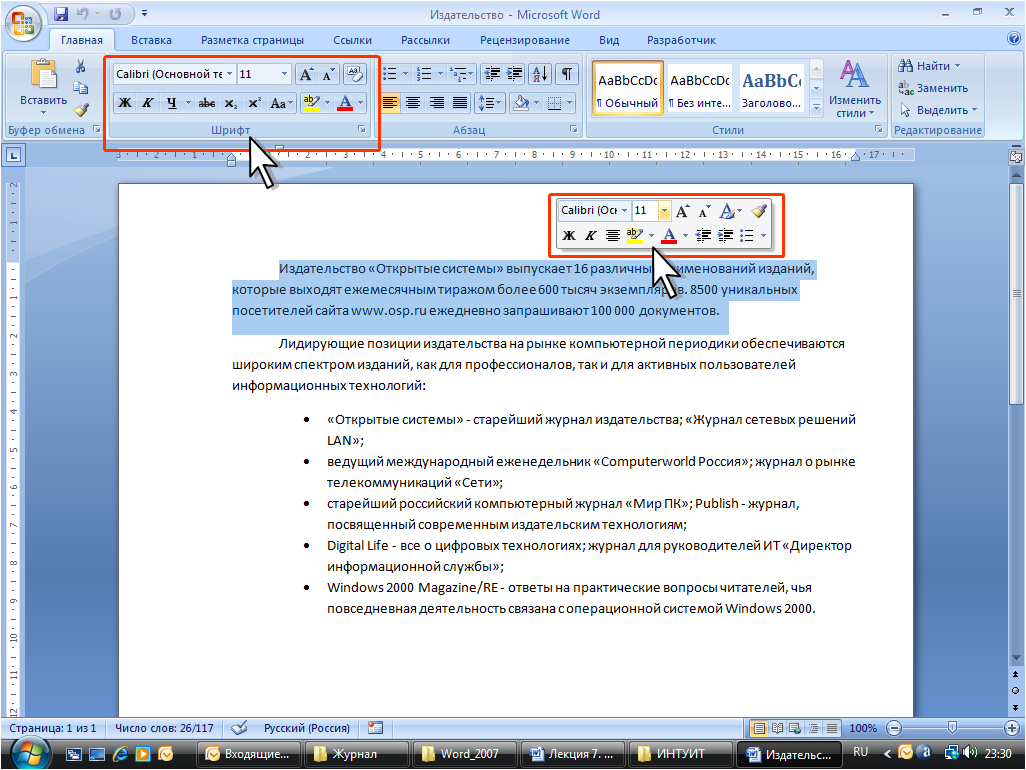
Как установить в word новые шрифты: Как установить новый шрифт в Word — Как установить новый шрифт в Windows 7, а также в Photoshop, Word, CorelDraw и другие программы
Как установить новый шрифт в Word — Как установить новый шрифт в Windows 7, а также в Photoshop, Word, CorelDraw и другие программы
Корпорация Microsoft постоянно трудится над усовершенствованием своего текстового редактора (Word). Ведется улучшение оптимизации, скорости отклика функций, а также постоянно добавляются всевозможные новые шрифты, которые своей красотой радуют глаз искушенным потребителям, однако всегда найдутся пользователи, которым будет недостаточно встроенного функционального набора. Поэтому существует безмерное количество дополнительных шрифтов разрабатываемые сторонними производителями и просто энтузиастами.
Однако, чтобы установить новый шрифт в среду Microsoft Office придется немного потрудится. Благодаря данной инструкции вы узнаете, как установить шрифт в ворд и с легкостью сможете проделать описанные ниже действия.
Скачивание нового шрифта
Перво-наперво в интернете необходимо найти тот самый желанный вами вордовский шрифт.
Стоит сразу отметить, что скачивать новый шрифт (собственно, как и любой сторонний софт) необходимо с проверенных сайтов.
Безопасные шрифты распространяются архивом, внутри которого запакован файл с расширением OTF или TTF (данный формат поддерживается операционной системой Windows и ничем сторонним его не открыть).
Инсталляция нового шрифта в ОС Windows
Теперь, когда файл-шрифт (расширение OTF или TTF) находится на вашем компьютере — необходимо инсталлировать скаченный шрифт в саму систему.
Для этого нужно открыть панель управления вашего компьютера. Если на вашем ноутбуке установлена новейшая операционная система Windows 8 или10, просто нажмите сочетание клавиш «Win+X», а после найдите в списке активную ссылку «Панель управления».
В более поздних версиях ОС Windows необходимо нажать на «Пуск», а после на «Панель управления».
Теперь необходимо найти раздел, позволяющий управлять шрифтами. Для его обнаружения вам необходимо найти и нажать на раздел «Оформление и персонализация», затем в новой вкладке вы обнаружите необходимый раздел «Шрифты».
Установка нового шрифта в Word
Теперь чтобы установить шрифт в ворде 2010 и 2016 годов (ворд 2007 и 2003 работает по такому же принципу, но с незначительными изменениями) необходимо запустить документ MS Word с ярлыка и найти в списке установленных шрифтов — новый. Для этого найдите на верхней панели незаметный значок, находящейся справа от раздела «Шрифт» и нажмите на него.
Это действие вызовет дополнительное контекстное окно, в котором нужно найти инсталлированный в систему шрифт и выбрать его нажатием ЛКМ. Затем нажмите «OK» и шрифт будет выбран. Теперь можно приступить к набору текста.
Теперь стоит понять дальнейшие действия. Если вы решили просто поэкспериментировать с новыми шрифтами или же вам нужно было распечатать красивый текст на своем принтере и сохранить его на бумаге, то на этом ваши действия закончены.
Исправить данное недоразумение можно, и даже очень легко.
Внедрение шрифта в документ
Для того чтобы ваш друг смог увидеть написанный вашим шрифтом текст, его необходимо внедрить в сохраняемый документ, что в свою очередь немного увеличит объем самого текстового файла.
Первым делом откройте пересылаемый документ, а после перейдите в его параметры. В открывшемся окошке выберите раздел «Сохранение» и поставьте галочку напротив «Внедрить шрифты в файл». Теперь нажмите «OK» после чего сохраните документ.
Готово, теперь его можно пересылать по почте всем своим знакомым.
Как установить шрифт по умолчанию
Для того чтобы каждый раз заново не искать новенький инсталлированный шрифт, имеет смысл сделать его «По умолчанию». Для этого откройте пустой текстовый документ. Затем сочетанием клавиш «Ctrl+D» вызовите дополнительное контекстное меню и из списка шрифтов выберите нужный, после чего нажмите на клавишу с названием «По умолчанию».
Сразу после этого выскочит еще одно окошко, где нужно выбрать строку, отвечающую за все документы и нажать «OK».
После этого все открывшиеся новые документы будут по умолчанию с этим шрифтом.
Вывод
В данной статье мы рассказали вам как установить на свой компьютер сторонний шрифт, с помощью которого можно написать, а после распечатать красивый и уникальный текст.
Также был рассмотрен вариант передачи сохраненного документа другому пользователю, на компьютер которого дополнительные шрифты не устанавливались, тем не менее текст был полностью читабелен.
Чтобы решить этот вопрос давайте рассмотрим несколько аспектов:
Общая информация
Все шрифты, которые доступны для использования в Word, находятся под управлением WINDOWS и для увеличения количества шрифтов в редакторе, необходимо их добавить в саму систему.